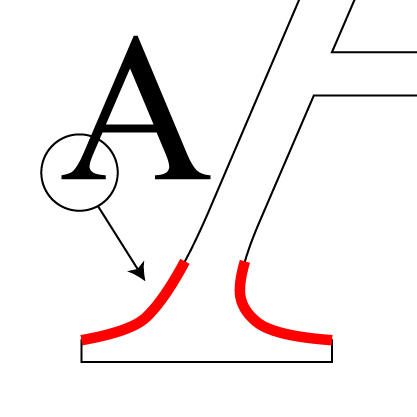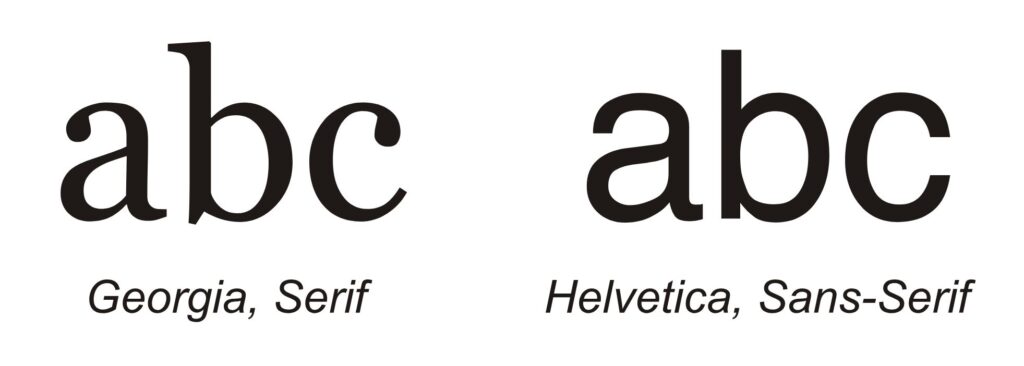
Serifen und serifenlos
Serifen sind die kleinen An- und Abstriche an Buchstabenenden, oft auch „Füßchen“ genannt. Sie können stark betont, dezent angedeutet, eckig oder rund auslaufen und verleihen Schriften einen charakteristischen Ausdruck. Während Serifenschriften traditionell im Buchdruck dominieren, verzichten Grotesk- bzw. serifenlose Schriften bewusst auf diese Gestaltungselemente.
Der Ursprung der Serifen ist umstritten: Manche führen sie auf Meißeltechniken beim Steinritzen zurück, andere auf den Gebrauch von Feder und Tinte. Edward Catich sah ihren Ursprung in der Gravurtechnik und machte diese Theorie in The Origin of the Serif bekannt.
Die Diskussion „Serif oder Sans Serif“ begleitet die Typografie bis heute. Befürworter von Serifenschriften betonen deren bessere Lesbarkeit in langen Texten, da Serifen das Auge entlang der Zeile führen und Kontraste in der Strichstärke den Lesefluss unterstützen. Serifenlose Schriften gelten dagegen als sachlicher, klarer und sind besonders unter schwierigen Bedingungen – etwa auf Straßenschildern – gut lesbar. Kritiker weisen allerdings darauf hin, dass viele dieser Untersuchungen auf älteren Schriftarten basieren und moderne serifenlose Schriften nicht ausreichend berücksichtigen.
Besondere Aufmerksamkeit verdienen die humanistischen serifenlosen Schriften. Sie verbinden die Klarheit der Grotesken mit der Lesefreundlichkeit klassischer Serifenschriften. Beispiele wie die FF Profile von Martin Wenzel oder Schriften von Erik Spiekermann und Luc(as) de Groot zeigen, dass serifenlose Schriften längst nicht mehr ausschließlich „mechanisch“ oder „leblos“ wirken, sondern Wärme, Eleganz und Eigenständigkeit besitzen.
Am Ende lässt sich festhalten: Nicht die bloße Frage nach vorhandenen oder fehlenden Serifen ist entscheidend. Vielmehr bestimmt die Gesamtgestaltung einer Schrift – ihr Rhythmus, ihre Proportionen und ihr Stil – darüber, wie sie wirkt und eingesetzt werden sollte.